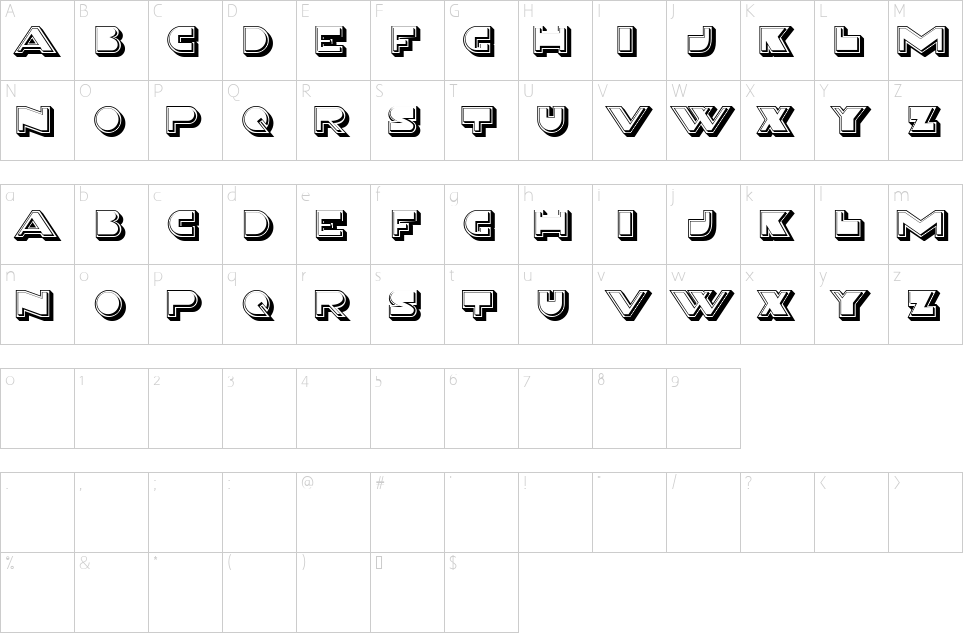
A fonte Miami é uma grata surpresa para designers gráficos em busca de uma variedade de opções de fontes gratuitas. Desenvolvida pelo designer Vladimir Nikolic, esta fonte oferece um estilo moderno e sofisticado para ilustrar e design web. Com uma vasta gama de letras, o Miami Font é perfeito para criar designs modernos e criativos. Descarregada centenas de vezes, a fonte é um recurso valioso para designers que buscam opções de fontes para seus projetos sem ter que desembolsar grandes quantias de dinheiro. Sem dúvida, a Miami Font é uma opção recomendada para quem busca uma fonte elegante e versátil.